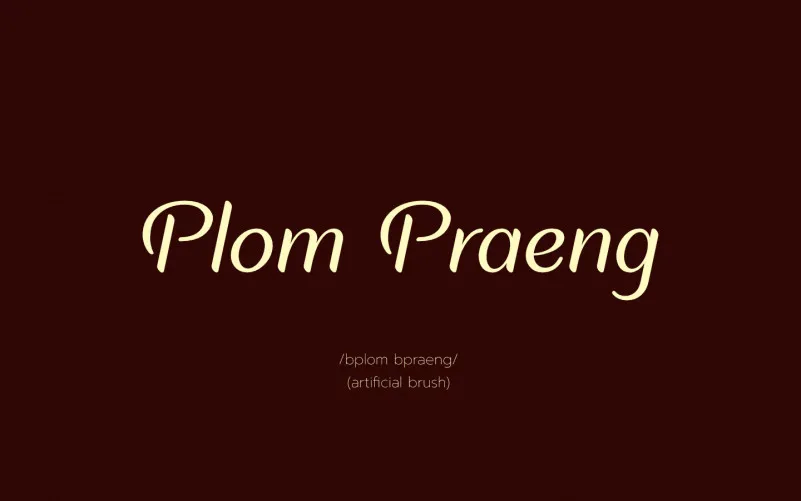
Aqui está uma versão adaptada para a página de download da font ‘Plom Praeng Script Font’, mantendo o tom informativo e convidativo: A ‘Plom Praeng Script Font’ é um estilo brush script que se destaca pela sua personalidade vibrante e expressiva. Criada pelo designer anupapjaichumnan, a fonte foi projetada para atender tanto quem usa gráficos profissionalmente quanto o amante do design desenho artístico. Com traços rústicos e expressivos, é uma escolha ideal para criações que buscam ser chamativas ou elegantes. Para aqueles interessados em usá-la comercialmente, há a opção de adquirir uma licença e um conjunto completo da fonte através do link mencionado. A ‘Plom Praeng Script Font’ não só oferece beleza visual impressionante, mas também flexibilidade na criação de textos personalizados. Seja você um estudante, designer profissional ou amante do design desenho artístico, a Plom Praeng Script é uma font que se destaca e certamente irá enriquecer seu trabalho. Se você desejar apoiar o desenvolvimento desta fonte, o canal de doação da página oferece um caminho fácil para contribuir. Essa fonte livre de direitos autorais para uso pessoal está disponível no website dos criadores, jipatype.com. Com essa fonte à sua disposição, é como se estivesse adquirindo um pedaço de arte digital em seu projeto próximo.